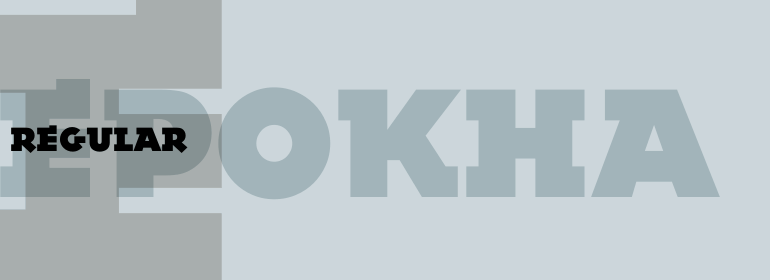
Epokha™
Epokha是Colin Brignall的作品,这是一种受20世纪初期海报风格影响的非常规粗衬线字体。其坚固的几何构造以崭新的现代方式吸引了人们的注意。Epokha通过多种替代字母形式变得更加灵活,为了达到最佳效果,它应该设置得更紧密。
Epokha is the work of Colin Brignall, an unusal slab serif typeface influenced by the poster styles of the early 20th century. Its robust geometric construction commands attention in a fresh, contemporary way. Epokha is made even more flexible by a number of alternative letter forms and should be set tightly for maximum effect.